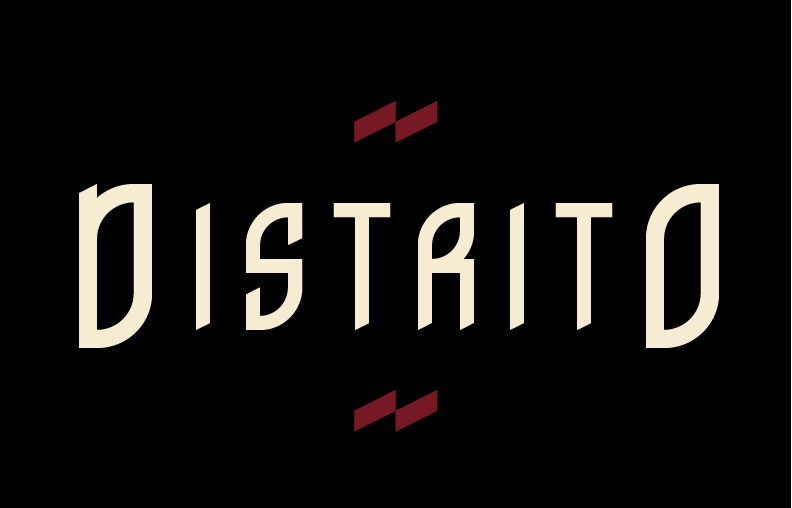
A Distrito Caps é uma fantástica nova adição à gama de fonts sans-serif que oferece uma mistura perfeita de modernidade e elegância para qualquer projeto de design gráfico, seja ele digital ou impresso. Desenvolvida pelo designer Hamilton, esta fonte traz consigo um estilo limpo e minimalista, que se adapta perfeitamente a diversos usos, desde headlines até textos menores sem perder a sua essência fresca e atemporal. Com uma tipografia de cabeça única e fluida, a Distrito Caps é ideal para projetos em constante evolução, onde um design inovador pode fazer toda a diferença. Suas formas curvas suaves combinam perfeitamente com linhas retas mais fortes para criar um equilíbrio visual interessante. Seja em websites responsivos ou materiais impressos de alto nível, esta fonte traz uma personalidade única que se destaca da multidão. Se você está buscando uma fonte que pode acompanhar o seu projeto por muitos anos sem perder sua relevância, a Distrito Caps é definitivamente um investimento valioso para qualquer designer ou editor. Com uma variedade de estilos e tamanhos compatíveis com a maioria das ferramentas de design, é fácil adaptá-la a seus próprios trabalhos. Assim, não apenas você poderá expressar sua criatividade através desta fonte única, mas também ajudará a criar um impacto duradouro em seu público-alvo.